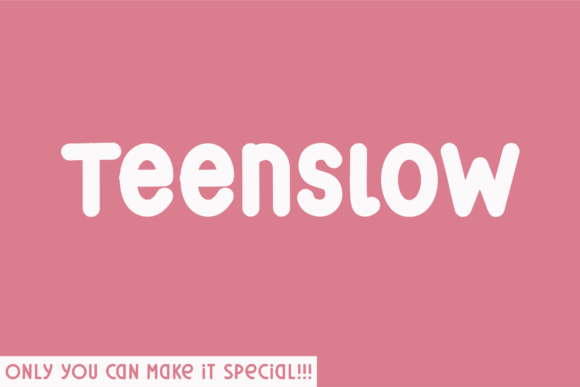
Teenslow Rounded
適切なデザイン要素を見つけるのは難しい場合がありますが、Teenslow Roundedは作品を即座に引き立てる優れたコレクションを提供します。
POD(オンデマンド印刷)製品、結婚式の招待状、またはソーシャルメディアのグラフィックを作成している場合でも、Teenslow Roundedは理想的です。